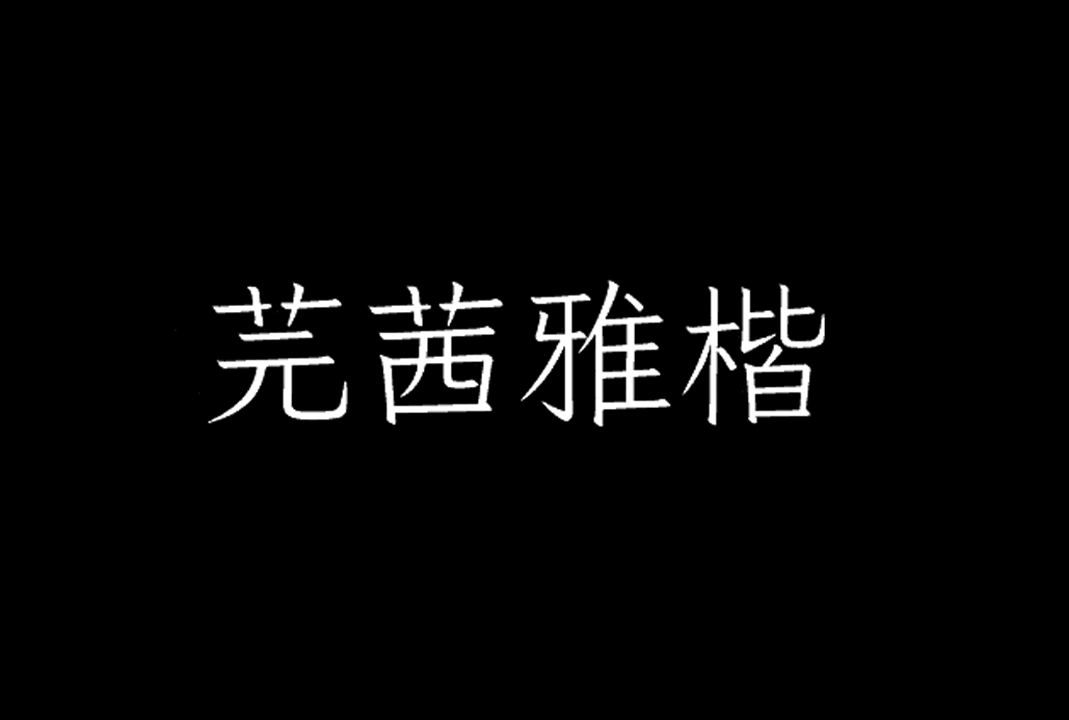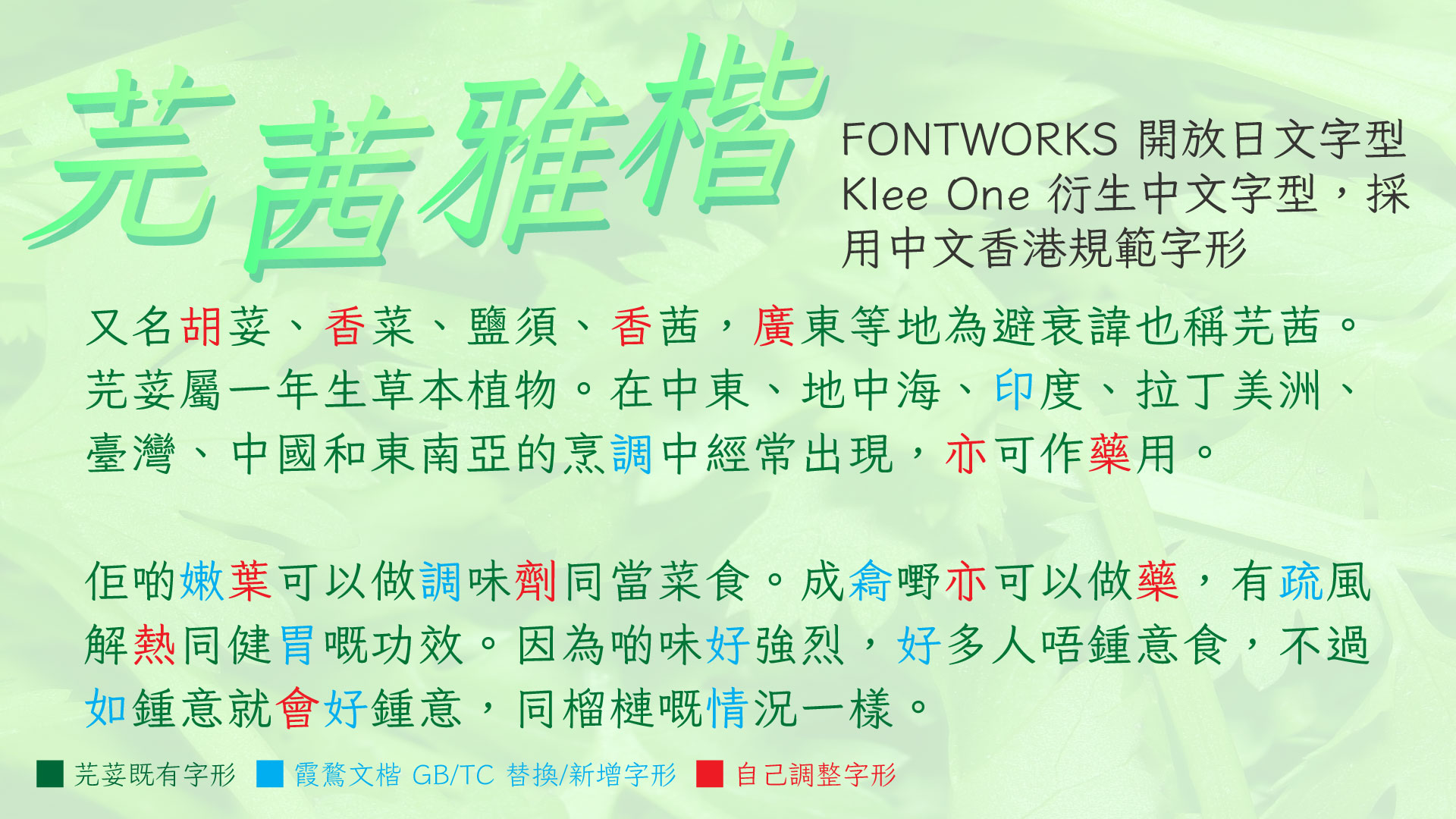
芫茜雅楷(JyunsaiKaai)免费字体开源字体下载
本字型在芫荽的基础上,加入霞鹜文楷 GB 和 霞鹜文楷 TC 所收录的汉字,并且尽可能调整字形贴近香港教育字形参考,总字数(汉字)高达约 15 000 个,适合任何学科领域的香港课本使用。
#1:截止发帖日,未完全调整来自霞鹜文楷 TC 的字形!
芫茜雅楷(JyunsaiKaai)示例,免费字体开源字体下载